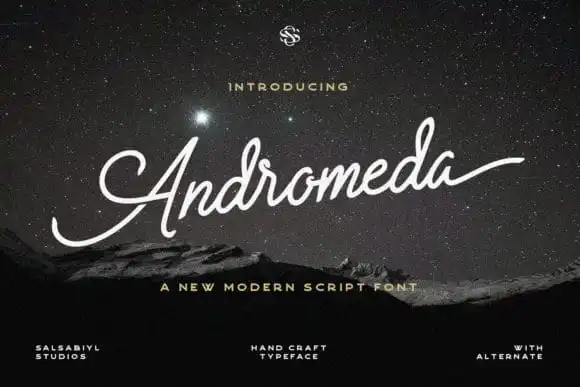
Andromeda Script Font
Andromeda Script é uma elegante fonte de script suave e limpa que parece ser capaz de transmitir sensações genuínas de arte manual. Seu designer, a studio salsabiylstudios, criou um recurso moderno e sofisticado para uso em projetos pessoais e branding. Com alternativas e swashes adicionais à disposição, esta fonte de script irá garantir que sua marca esteja sempre impressionante e profissional. Se você está planejando lançar seu próximo projeto pessoal ou branding digital, Andromeda Script é a escolha certa para um visual único e sofisticado sem desgastar seus recursos. Não hesite em dar vida à sua identidade com essa fonte de alta qualidade.